“体”是文字的形式特征,不同的字体会呈现出不同的字体风格,且不同的字体会在手写体字形设计中表达出不同的字体性格。从书法体角度来看,传统意义上字体分为篆体、隶书、草书、楷书、行书5种。
篆体
篆体中的很多字都属于象形文字,篆体也是我国最古老的书体,笔画粗细一致,形体平正,横平竖直。字体形式严谨工整,无论是单个笔画还是整体的单字结构都以圆为主。
隶书
隶书由篆体发展而来,由篆体化繁为简,化圆为方,化弧为直。字形结构呈宽扁,横长竖短,整体的视觉感更为秀丽端庄。
草书
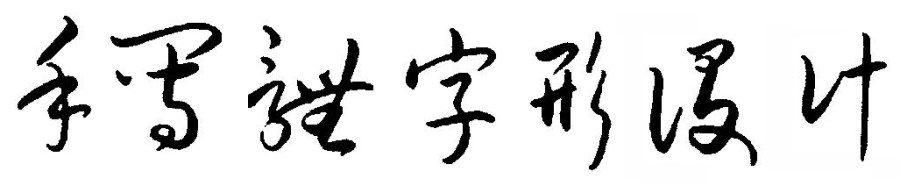
草书的特点是结构简省,笔画连绵,是为了书写简便性而由隶书演变而来的,字与字之间的笔势相互迎合,偏旁部首逐渐发展得更为简化并形成互借,发展至今草书的审美价值已经远远超越了其使用价值。
楷书
楷书是汉字沿用至今的主要书体。楷书的每个笔画结构都清晰明确,笔画起收有序,整体工整规范。在字形结构上,楷书强调均衡分布、重心平稳、比例适当,是汉字的标准字体。
行书
行书介于草书和楷书之间,既有楷书的沉稳结构,又具备草书的简洁流畅。行书的字体风格轻盈流动,在点画的各种形态上都表现得较为明显,字形的笔画之间相互牵连,适用性极强。